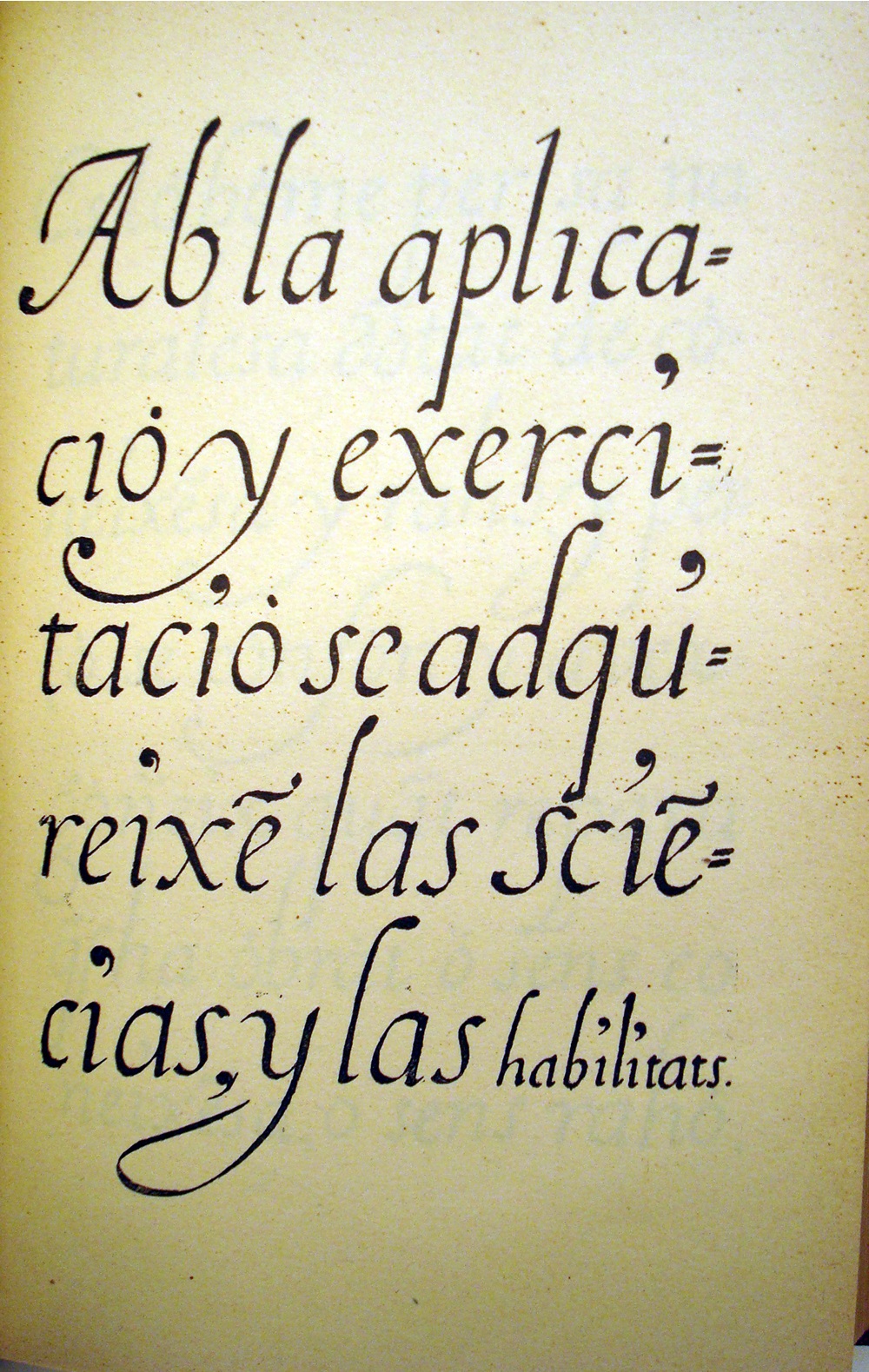
Ya hacía mucho tiempo que queríamos desde Bibliotypes rendir un pequeño homenaje a uno de los pocos calígrafos que aún existen en nuestro país: Oriol Miró. (clicar para ver impresionantes trabajos)
Cuando nos conocimos personalmente hace unos años nuestra intención era la de poder encargarle un libro con todas las formas de letras y también con muestras de creación propia o experimental escritas en catalán, ya que por desgracia muchos calígrafos y tratadistas no utilizaron esta lengua para sus trabajos.
(Ver Apéndice). La crisis ha dejado este proyecto que iniciamos con mucha ilusión en un "standby" esperando tiempos mejores.
Las primeras cinco láminas que encargamos a este magnífico artista son 2 dedicadas a la escritura romana y tres dedicadas a la escritura cancilleresca, así pues, aquí quedan reproducidas, esperando poder seguir mas adelante con este proyecto.
| Abecedario en letra Romana, por Oriol Miró |
| Letra Cancilleresca por Oriol Miró |
| Abecedario de Fantasía en cancilleresca por Oriol Miró |
Las muestras son de un claro y seguro trazo y demuestran un dominio no solo de la ejecución de las letras, si no también de la buena composición y organización de la lámina. Nuestra admiración y los mejores deseos profesionales a este magnífico artista desde este blog.
Apéndice Histórico:
En de la historia de la bibliografía catalana, aunque han existido muy buenos calígrafos, solo se conocen dos libros publicado en catalán sobre el tema hasta el s. XX:
- El primero escrito por Antoni Eudald Llaguna y de título: "Primera part del art de escriurer intitulas descans" y publicado por Pere Lacavalleria en Barcelona,1640. De este libro solo se conservan escasos ejemplares: un ejemplar en Cambridge (Mass.) Houghton library en la Universidad de Harvard, y otro en la Biblioteca de la Universidad de Barcelona (UB), desconozco otros ejemplares.
- También encontramos algunas muestras pero muy simples en catalán en el libro de Baldiri Rexach "Instruccions per la Ensenyança de Minyons" publicado en Gerona por Anton Oliva 1749. Este libro tuvo once ediciones hasta entrado el siglo XIX y desde la sexta edición las láminas caligráficas se editaron en idioma castellano. Fue el libro de referencia en la educación básica durante mas de 50 años y como no, tenía un pequeño apartado dedicado a la caligrafía, con unas láminas de muestras y unas recetas de tintas.
Las muestras son de factura un poco tosca y fueron grabadas por diferentes grabadores según la edición. Reproduzco las láminas de la 1ª edición facsímil del año 1923, las cuales son un poco mas grandes de tamaño ya que se reprodujo ampliado y fueron grabadas por Igtatius Vall en Barcelona y también las láminas diferentes de la décima edición, ca. 1803, grabadas por Vilanova F.
Láminas de la 1 edición de 1749 del libro de Baldiri Rexach: (Versión facsímil de 1923 impresa por O. Viader)
Láminas de la 10 edición de pricípios del s. XIX (1803) del libro de Baldiri Rexach, publicada por Agustí Figaró en Gerona:
| Detalle de la lámina anterior por Oriol Miró |